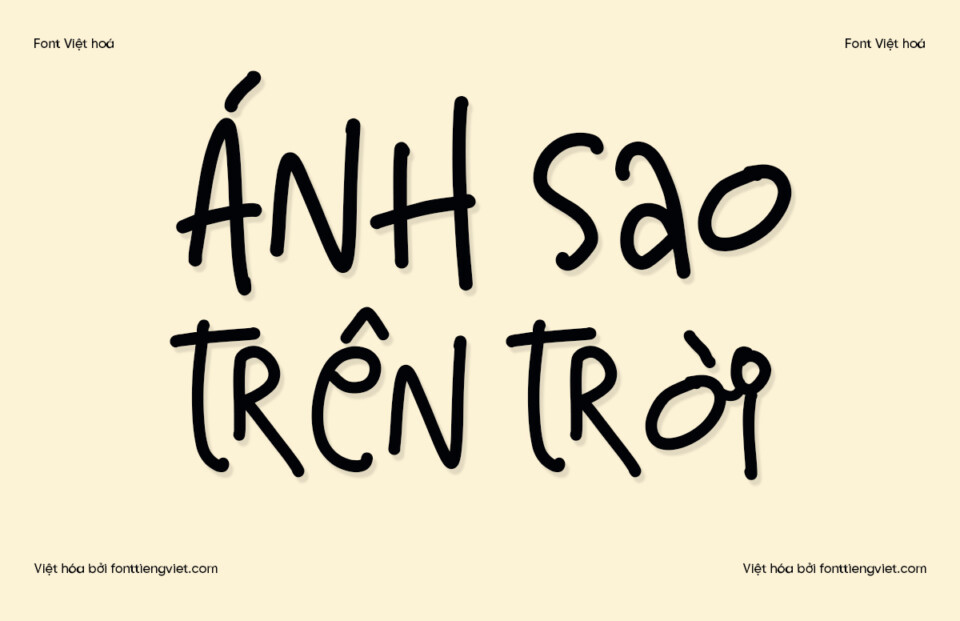
Font Việt hóa 1FTV VIP Kindly Crunch – Font chữ dễ thương, nổi bật cho tiêu đề
Font Việt hóa 1FTV VIP Kindly Crunch là lựa chọn rất “đã mắt” nếu bạn đang cần một kiểu chữ display dễ thương, dày dặn và có độ nhấn mạnh tốt trên mọi bố cục. Nhờ nét chữ tròn, vui nhộn và cảm giác “giòn” đúng như tên gọi, Kindly Crunch đặc biệt phù hợp cho các thiết kế mang năng lượng tích cực: poster sự kiện, banner khuyến mãi, bìa social, nhãn dán (sticker), bao bì sản phẩm và branding phong cách trẻ trung.
Điểm nổi bật của Font Việt hóa 1FTV VIP Kindly Crunch
Điểm mạnh lớn nhất của Kindly Crunch Việt hóa nằm ở khả năng tạo tiêu đề nổi bật mà vẫn giữ được sự thân thiện. Font có cấu trúc chữ dày, dễ đọc ở khoảng cách xa, nên khi đặt trên nền màu hoặc background có họa tiết vẫn “ăn” tốt. Bên cạnh đó, bản Việt hóa giúp bạn gõ tiếng Việt mượt mà, tiết kiệm thời gian chỉnh sửa khi làm ấn phẩm marketing.
Font Kindly Crunch Việt hóa hợp với thiết kế nào?
Nếu bạn đang phân vân dùng font cho dự án nào, dưới đây là các tình huống mà font Việt hóa 1FTV VIP Kindly Crunch phát huy hiệu quả:
- Poster, banner, standee: tiêu đề sale, sự kiện, khai trương.
- Thiết kế social: thumbnail, cover Facebook/YouTube, bài đăng “call to action”.
- Packaging & sticker: nhãn mác sản phẩm handmade, đồ ăn vặt, quà tặng.
- Menu quán & bảng giá: tạo cảm giác thân thiện, bắt mắt.
- Branding trẻ trung: logo mini, tagline, headline trong bộ nhận diện.
Gợi ý phối font & màu sắc để “đẹp nhanh”
Để Kindly Crunch nổi bật đúng chất, bạn nên dùng font này cho headline hoặc chữ ngắn. Phần nội dung dài có thể phối cùng một font sans Việt hóa gọn gàng để cân bằng. Về màu sắc, các tông rực (cam, vàng, hồng, xanh mint) hoặc phối tương phản (đậm – sáng) sẽ làm font “bật” lên mạnh hơn. Khi cần cá tính hơn, bạn có thể thêm viền (stroke) mỏng hoặc bóng nhẹ cho chữ.